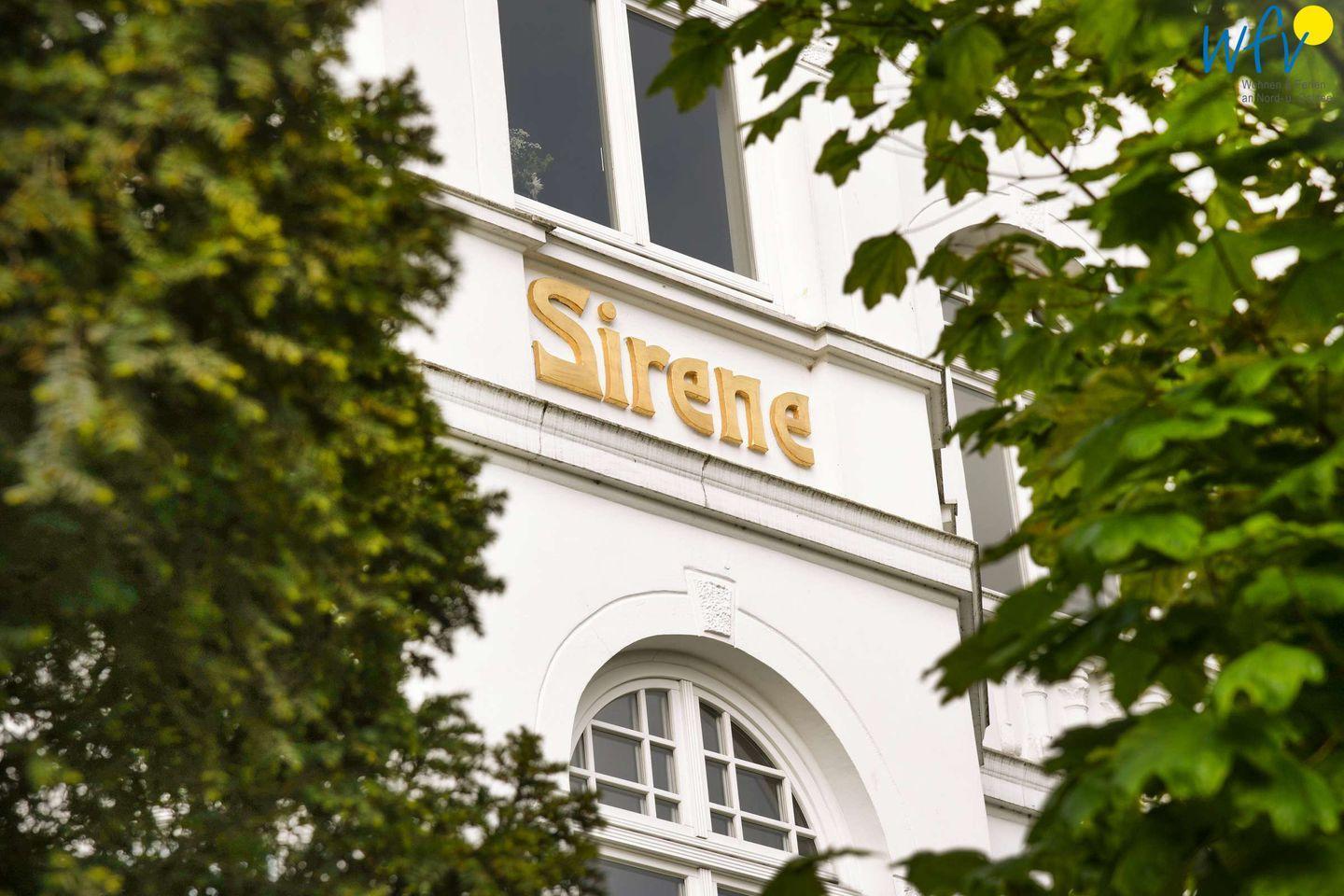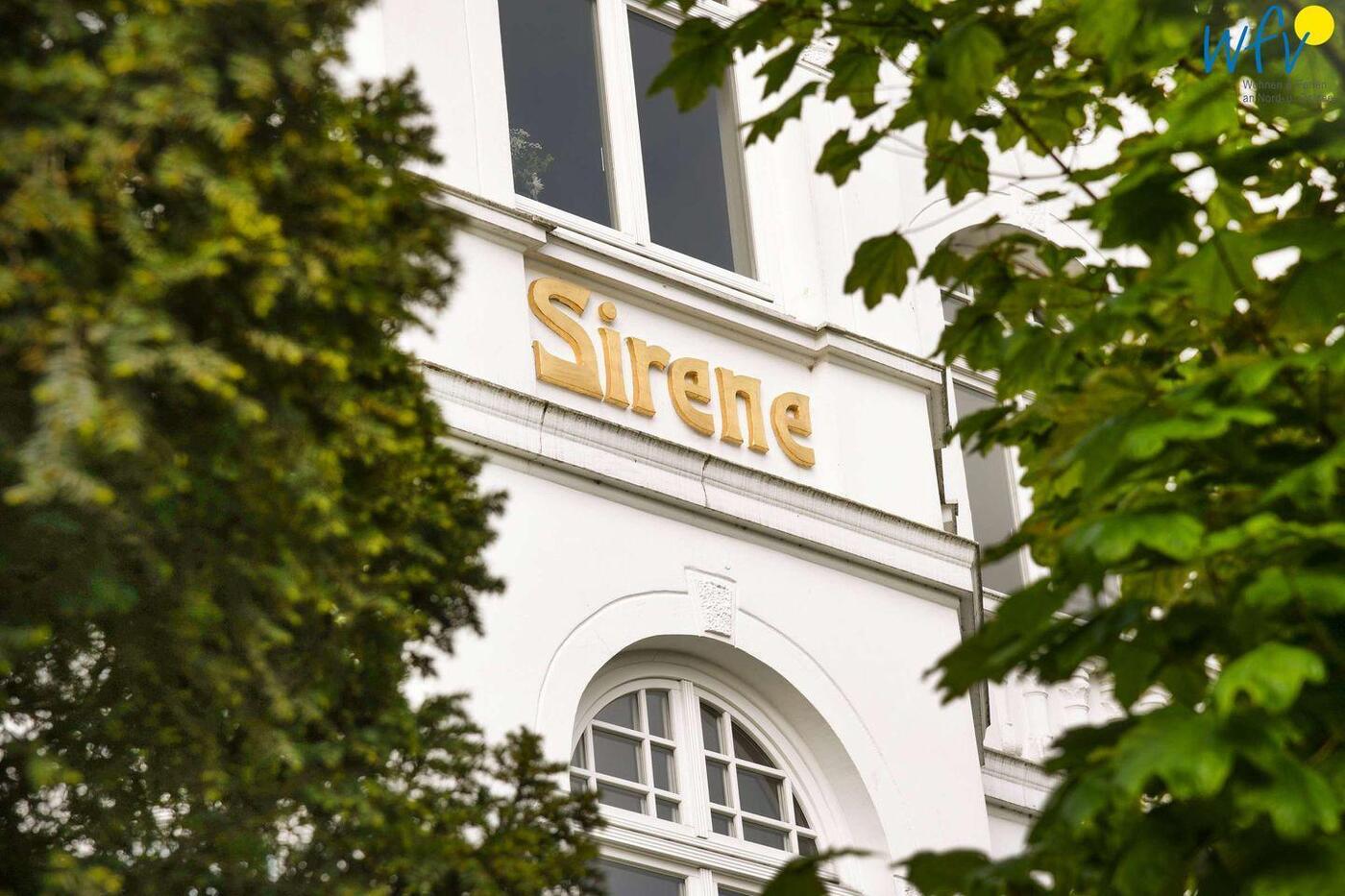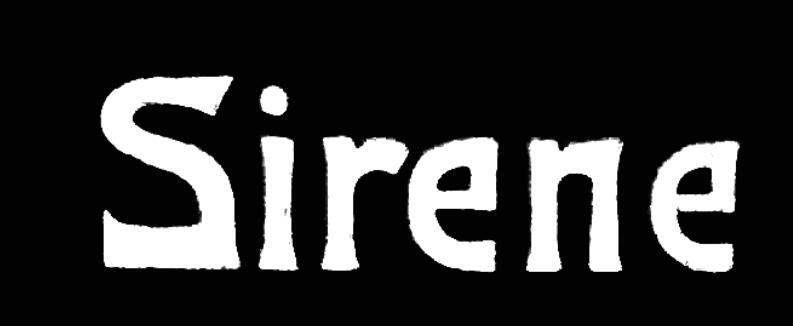
[Sirene Villa] Diese Jugendstil Typo bitte?
wtf, wfi und chatGPT konnten leider bisher keine Treffer erzielen. Ich freue mich auf des Rätsels Lösung und sage Dankeschön im Voraus.
Hallo @hhf, bei einer authentischen Beschriftung aus der Zeit wird der Schriftzug für diese Stelle handgemacht sein und nicht auf einer Satzschrift basieren – in der Jugendstil-Ära gab es nicht die heutigen Möglichkeiten, Druckschriften auf beliebige Größen hochzudimensionieren. Die entsprechenden Gewerke in Architekturbeschriftung/Steinmetzarbeiten bzw. Steinbildhauerei und Schildermalerei waren separiert vom Buchdruck. Der Standardartikel hierzu: